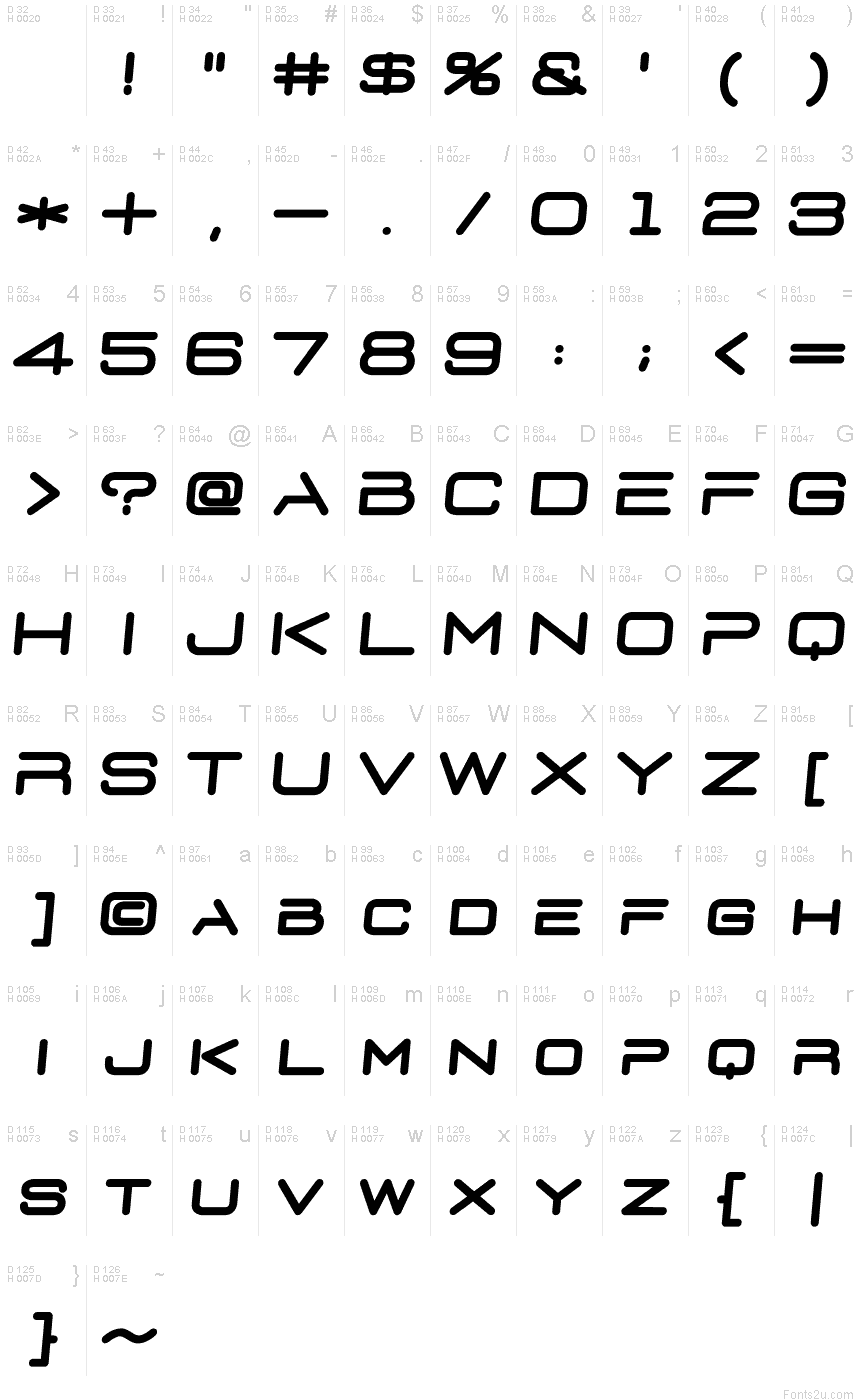
D3 Euronism Bold italic
D3 Euronism Bold italic od DigitalDreamDesign to darmowy, nowoczesny font typu display o eleganckim, futurystycznym sznycie. Szerokie, zaokrąglone kształty, zdecydowane pochylenie i płynne, niemal ciekłe krzywe sprawiają, że każde słowo wygląda, jakby pochodziło z futurystycznej deski rozdzielczej lub prototypu auta koncepcyjnego. Pogrubiona odmiana zapewnia wyrazisty i czytelny wygląd nawet na tle skomplikowanych grafik czy świecących gradientów.
D3 Euronism Bold italic świetnie sprawdzi się, gdy chcesz dodać energii logotypom e-sportowym, plakatom wyścigowym, brandingowi technologicznemu, nakładkom streamingowym, ulotkom czy futurystycznym makietom UI. Ten darmowy krój pisma najlepiej prezentuje się w dużych nagłówkach i znakach graficznych; w tekstach głównych postaw na lekki, czysty font bezszeryfowy, aby jego błyszcząca, dynamiczna osobowość mogła w pełni wybrzmieć.